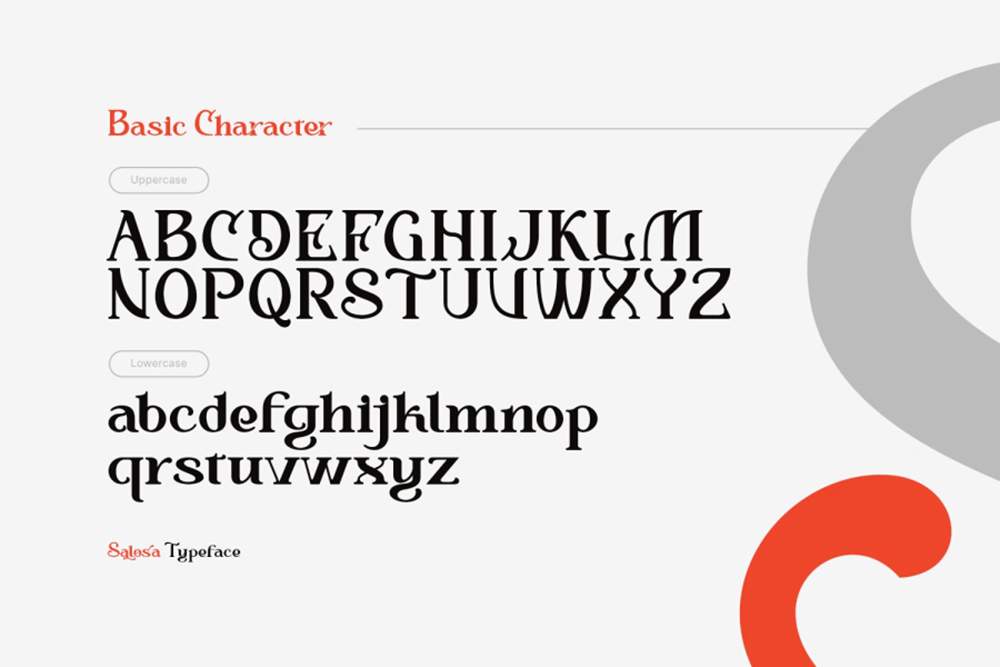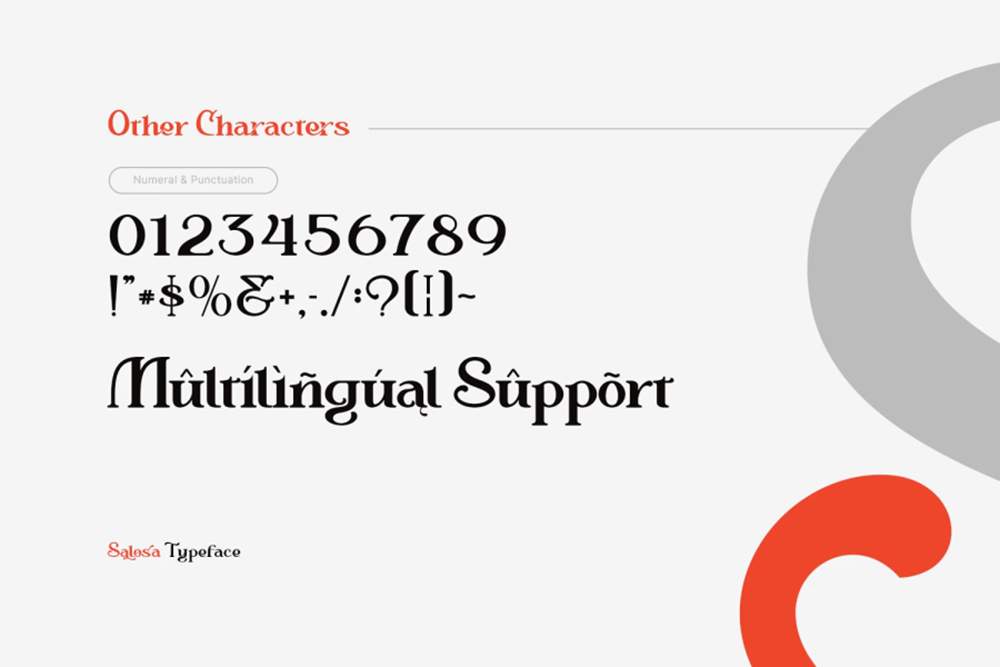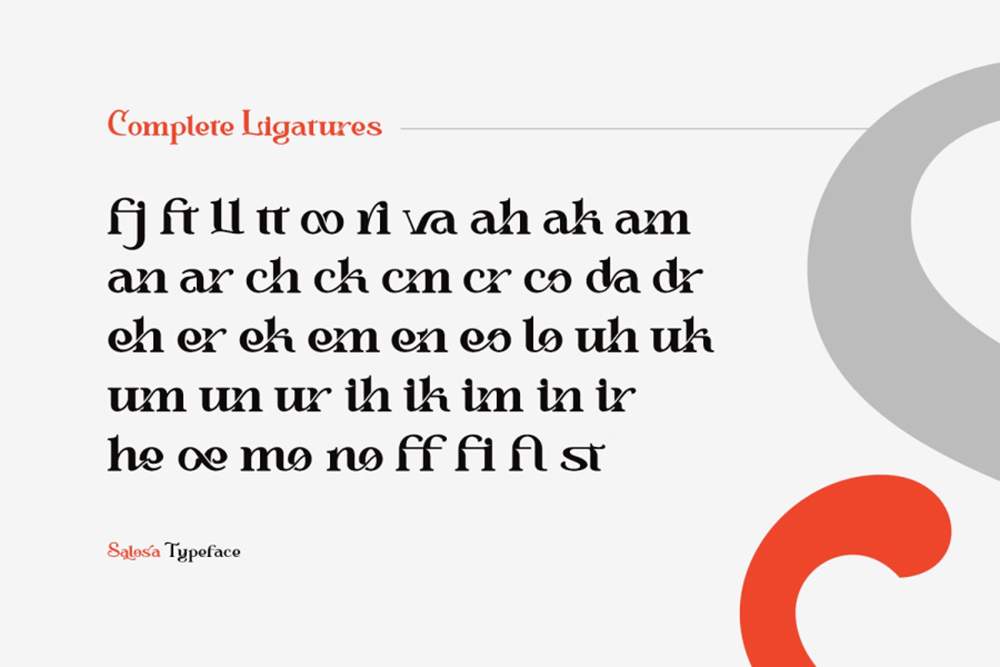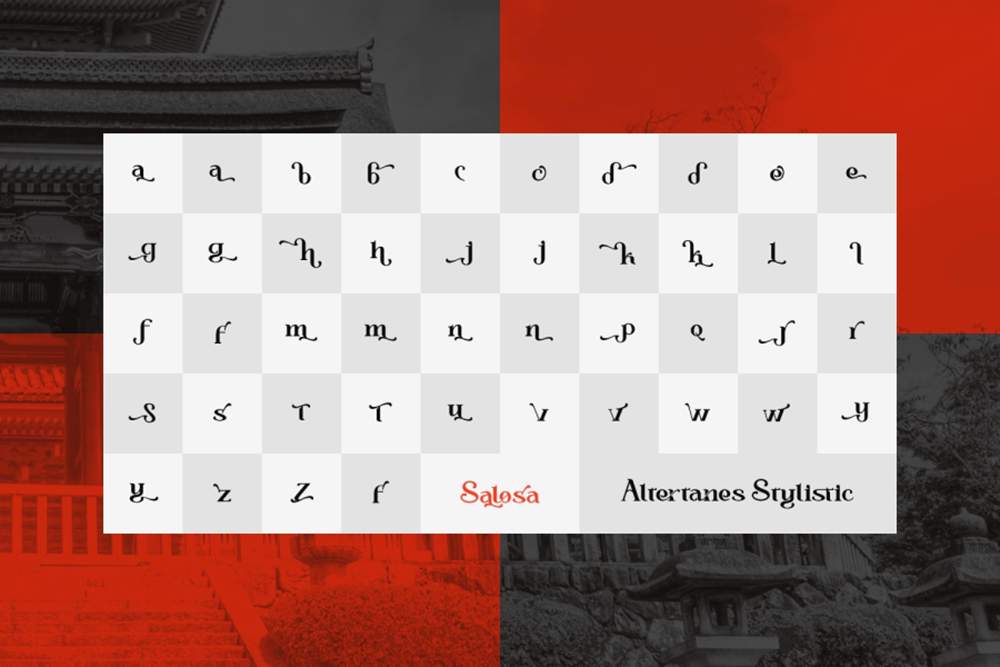
دانلود فونت انگلیسی Salosa Font
فونت پرمیوم و انگلیسی Salosa Font یک فونت پیچیده و همهکاره است که ظرافت کلاسیک را با خوانایی مدرن ترکیب میکند. Salosa که با سریفهای اصلاحشده و تناسبات متعادل طراحی شده است، حرفهای بودن و جذابیت بیزمان را به نمایش میگذارد و آن را برای طراحی سرمقاله، برندسازی و بستهبندی لوکس ایدهآل میکند. خطوط تمیز و کنتراست ظریف آن، خوانایی عالی را در رسانههای چاپی و دیجیتال تضمین میکند، در حالی که جزئیات برازنده آن، به تیترها، لوگوها و متن بدنه، جلوهای از ظرافت میبخشد. چه برای مجلات مد سطح بالا، هویتهای سازمانی یا دعوتنامههای زیبا استفاده شود، Salosa حضوری آراسته و معتبر ارائه میدهد. حروف هماهنگ و مجموعه کاراکترهای گسترده این فونت از چندین زبان و نیازهای طراحی پشتیبانی میکند و انعطافپذیری را برای پروژههای خلاقانه ارائه میدهد. Salosa با تعادل کامل سنت و ذوق معاصر، هر طرحی را با پیچیدگی و جذابیتی ماندگار ارتقا میدهد.
مزایای استفاده از فونت لاتین Salosa چیست؟